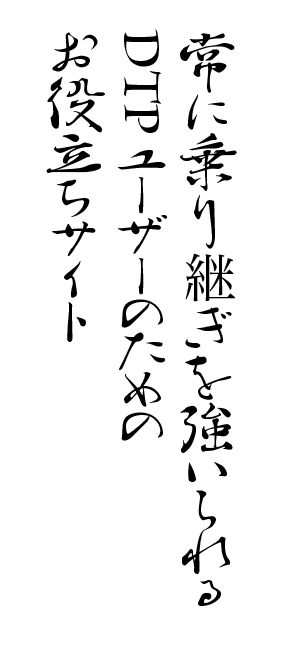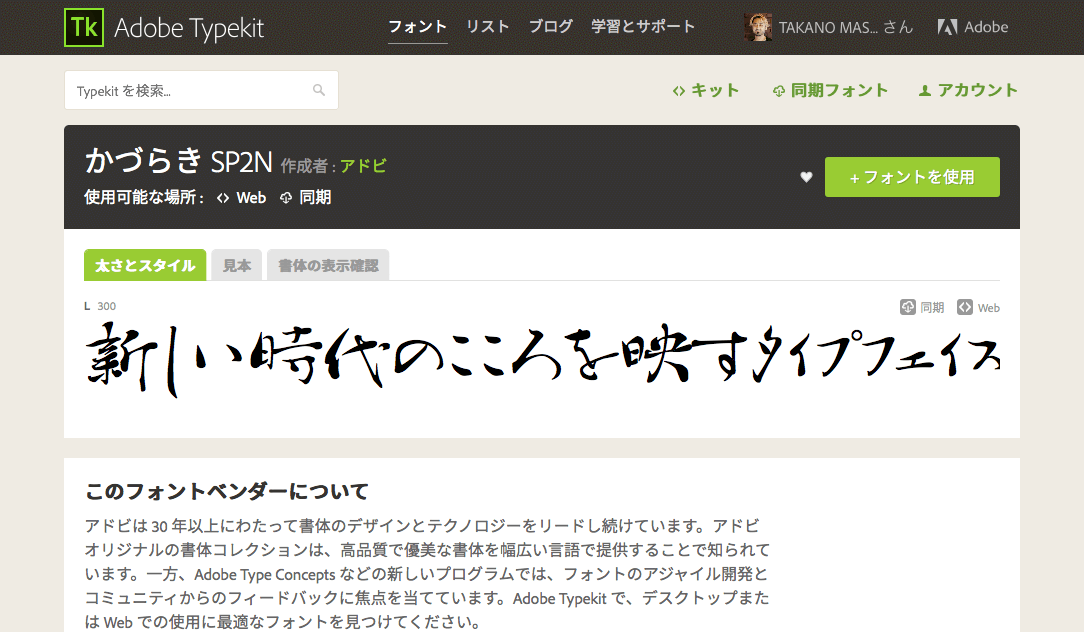
アドビから新書体「かづらきフォント」がリリース
日本語フォントは、仮想ボディと呼ばれる正方形のグリッド内にデザインされていますが、この「かずらき」は文字ごとに文字の幅や高さが異なります(右は、かずらきを使ってIllustratorで組んだもの:カーニングは「0」に設定。「継」だけ明朝になっていますが、かづらきは、すべての字体を持っているわけではありません)。
また、「この」「これ」「こと」「して」などは「合字」扱いで一続きの文字として表現されるようになっているとのことです。